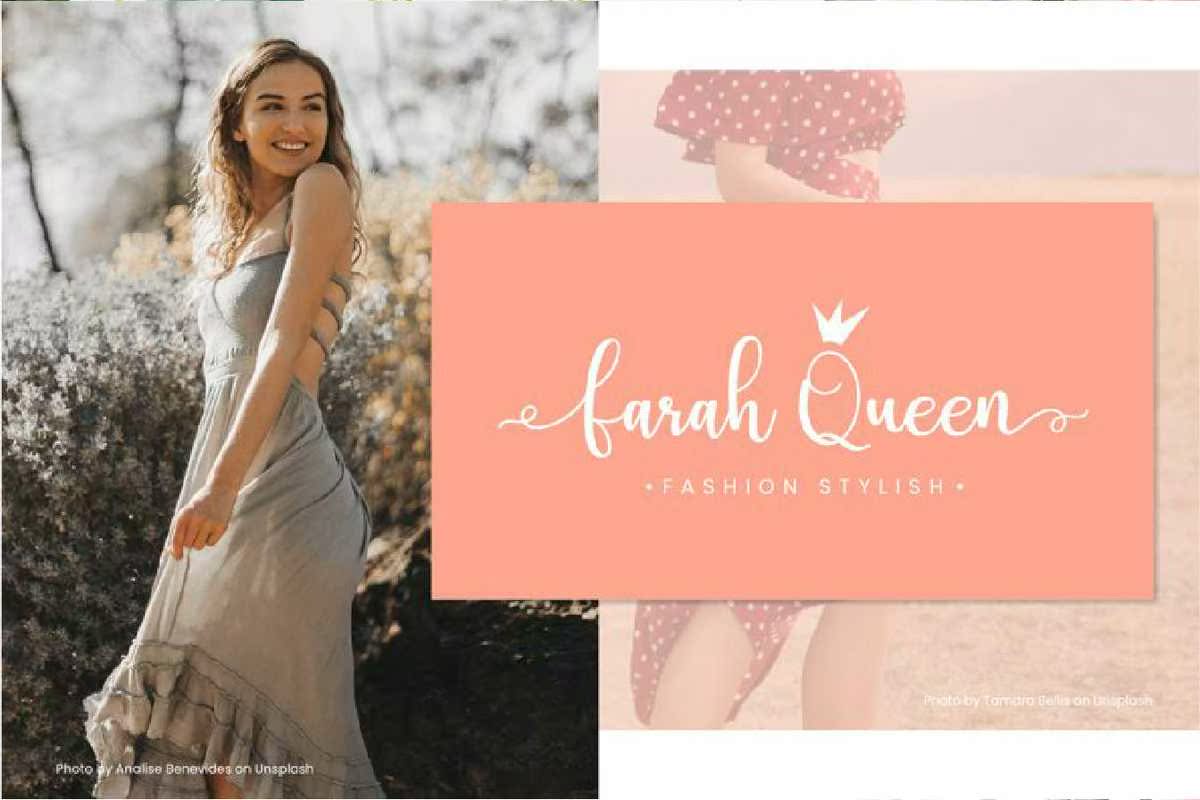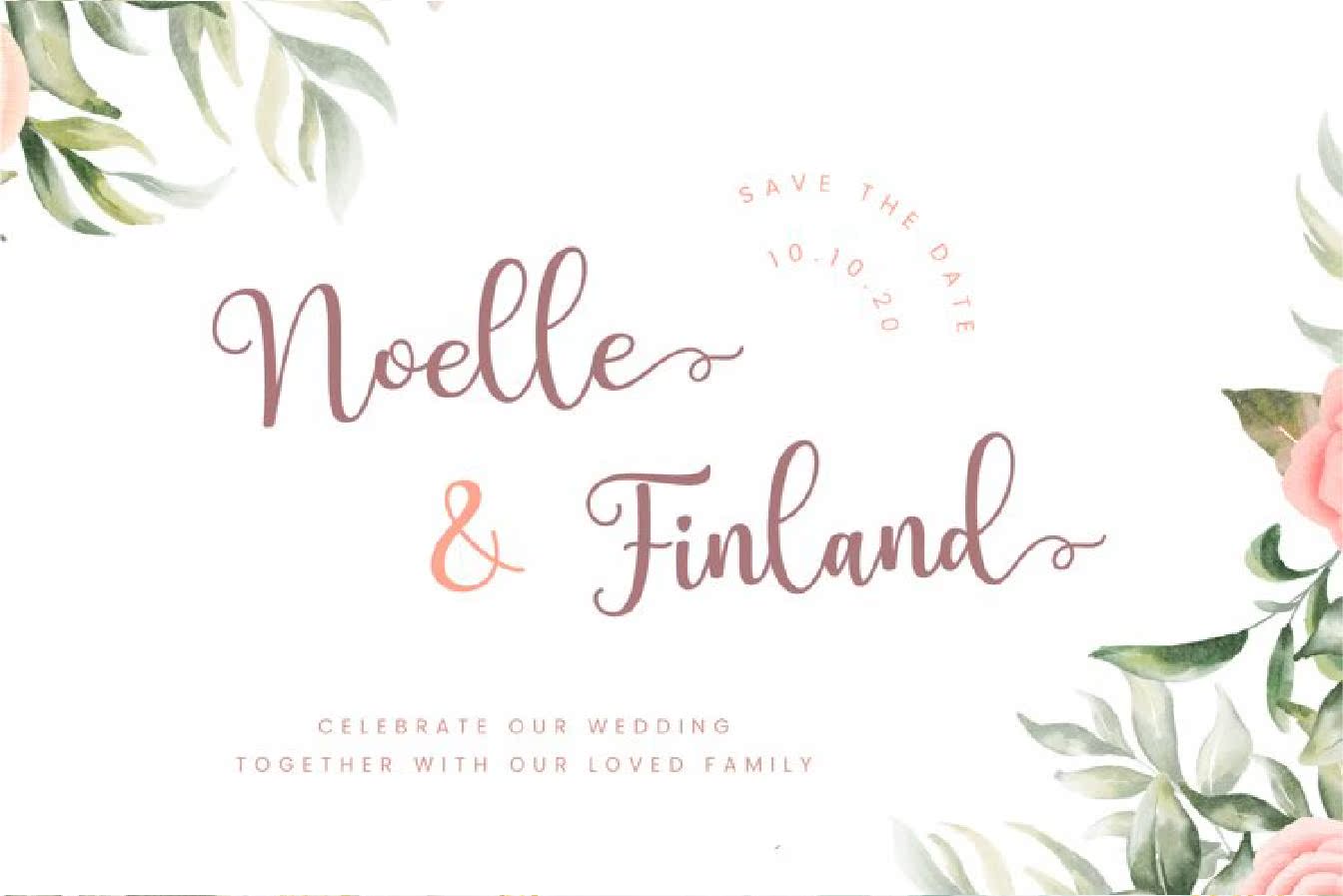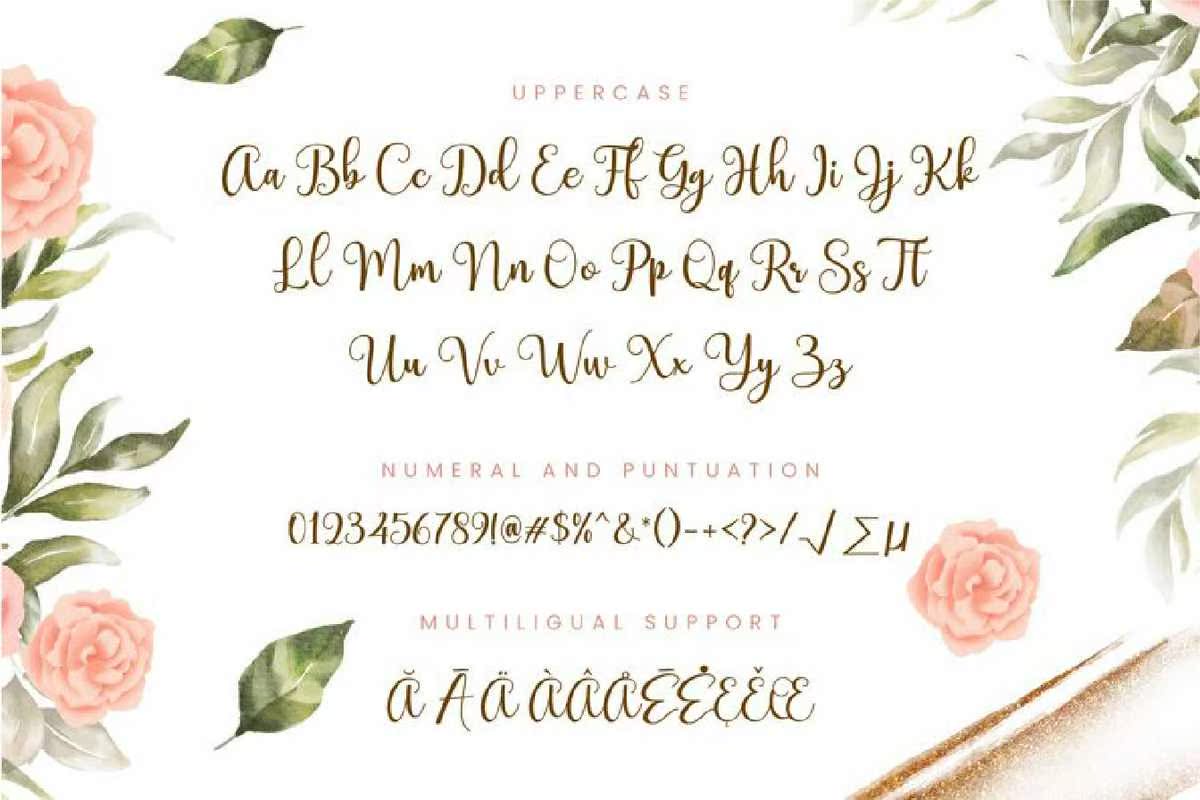
CharmLatten是一款为支持您的精彩项目而设计的可存储手写字体。CharmLatten是品牌项目、徽标、婚礼设计、社交媒体、广告、产品包装、产品设计、标签、照片、水印、邀请函、文具、,以及任何需要美观的现代和书写风格的项目。Charm格式是一种为支持您的伟大项目而设计的可存储手写格式。Charm格式适用于品牌项目、徽标、婚礼设计、社交媒体、广告、产品包装、产品设计、标签、照片、水印、邀请函、文具、,以及任何需要优美的现代风格和写作风格的项目。